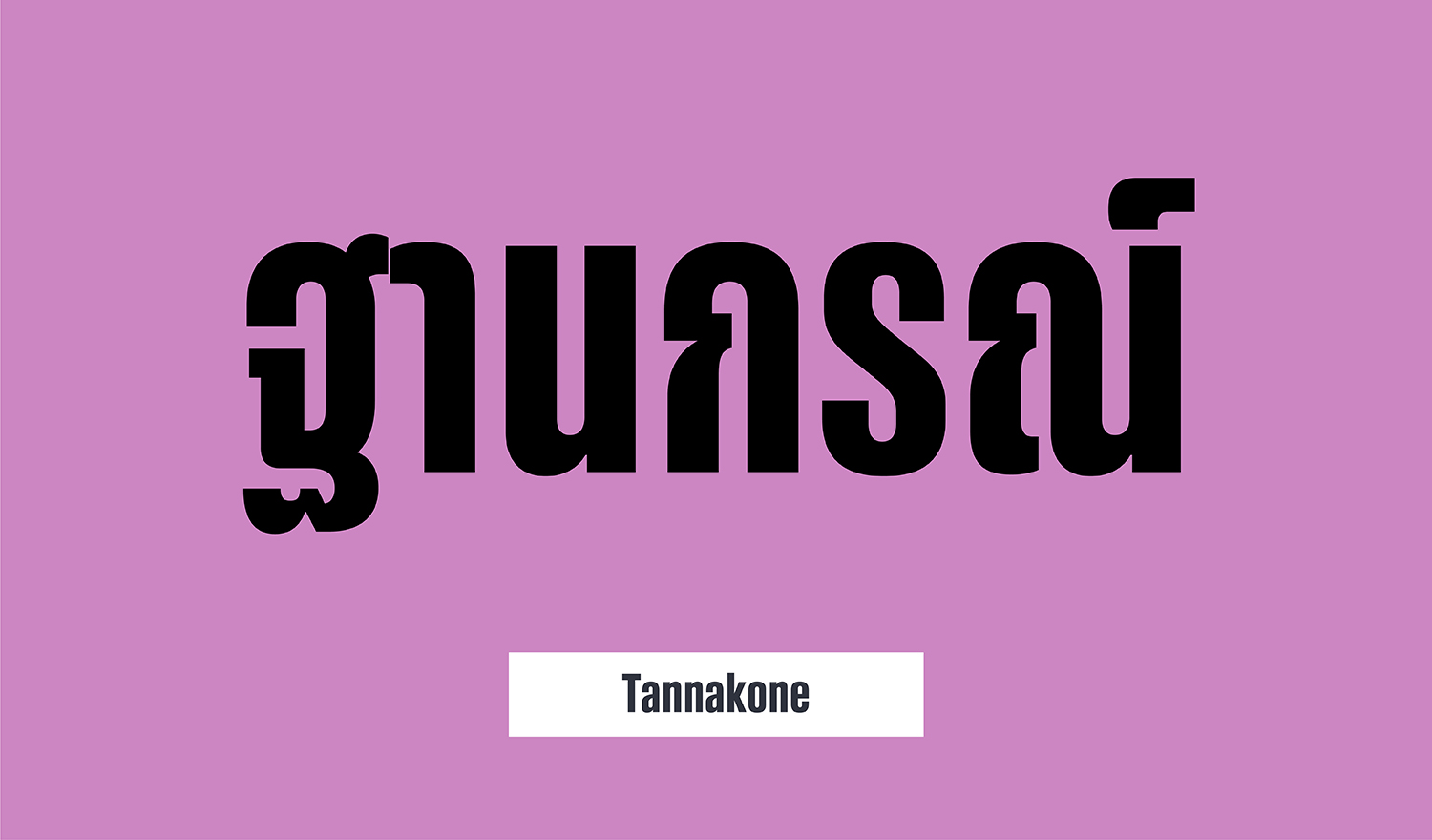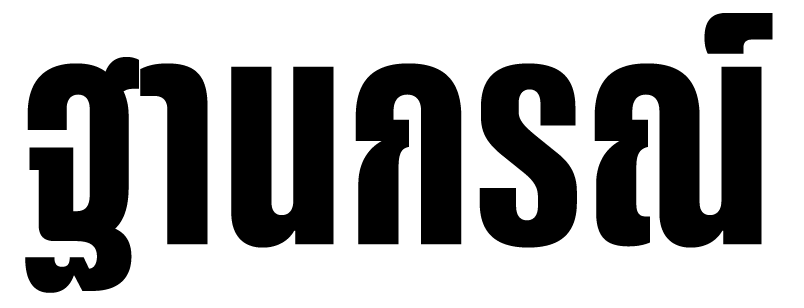
Tannakone
타나콘은 결코 일반적이지 않은 독특한 디자인의 수퍼 컨덴스드 폰트입니다.
이처럼 좁은 너비로 제작된 태국어 폰트가 많지 않습니다.
타나콘은 좁은 너비의 태국어 문자가 필요한 경우 가장 최적의 선택이 될 것입니다.
이는 라틴의 컨덴스트 폰트와 대응하여 나란히 사용하기 좋습니다.